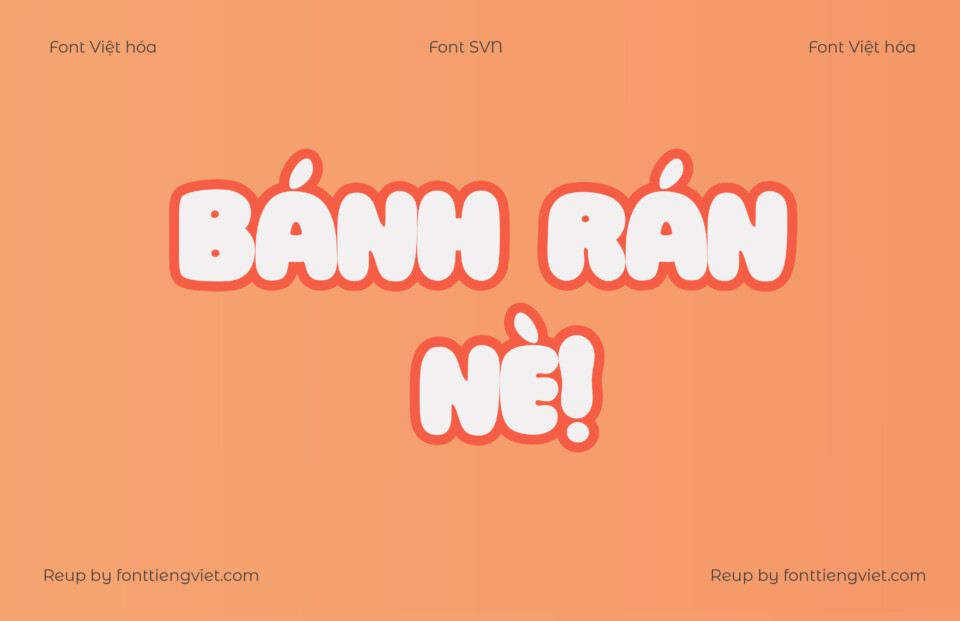
Tải Font Việt hóa SVN Ziclets Miễn Phí Cho Thiết Kế Sáng Tạo
Trong thế giới đồ họa hiện đại, việc lựa chọn Font Miễn Phí chất lượng đóng vai trò then chốt trong việc tạo nên dấu ấn riêng biệt cho mỗi tác phẩm. Font Việt hóa SVN Ziclets nổi lên như một sự lựa chọn hàng đầu cho những ai yêu thích phong cách trẻ trung và đầy năng lượng. Bộ phông chữ này không chỉ giữ nguyên nét cá tính của bản gốc mà còn được tối ưu hóa hoàn toàn cho tiếng Việt, giúp người dùng dễ dàng thể hiện ý tưởng mà không lo lỗi hiển thị ký tự đặc biệt.
Đặc điểm nổi bật của Font Việt hóa SVN Ziclets
Thiết kế độc đáo và phá cách
SVN Ziclets sở hữu những đường nét uốn lượn mềm mại nhưng vẫn giữ được sự chắc chắn trong cấu trúc chữ. Đây là kiểu chữ mang hơi hướng retro kết hợp phong cách hiện đại, rất phù hợp cho các poster sự kiện trường học hoặc bìa sách thiếu nhi. Sự linh hoạt của Font Việt hóa SVN Ziclets cho phép các bạn học sinh và giáo viên sáng tạo ra những slide bài giảng hấp dẫn, thu hút sự chú ý của người xem ngay từ cái nhìn đầu tiên.
Khả năng ứng dụng đa dạng
Bên cạnh việc dùng cho giáo dục, bộ font này còn cực kỳ hiệu quả trong thiết kế logo, bao bì sản phẩm hay các ấn phẩm truyền thông mạng xã hội. Nhờ được Việt hóa kỹ lưỡng bởi đội ngũ SVN, các dấu câu được đặt vị trí chuẩn xác, mang lại sự cân đối tuyệt vời cho văn bản.